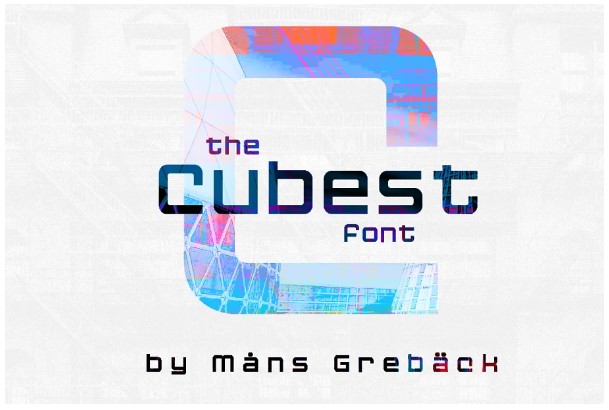
Creativemarket Cubest Font
[Creativemarket] Cubest Font
Cubest - это геометрический шрифт sans-serif.
Созданный Мансом Гребеком в 2021 году, этот футуристический шрифт имеет квадратный, монолитный вид с ретро-цифровым стилем.
Семейство состоит из восьми стилей: Cubest Monospace и Cubest Variable, в дополнение к Light, Medium и Bold, а также каждый вес в виде Italic.
Шрифт поддерживает все европейские языки на основе латиницы и содержит все символы, знаки, пунктуацию и цифры.